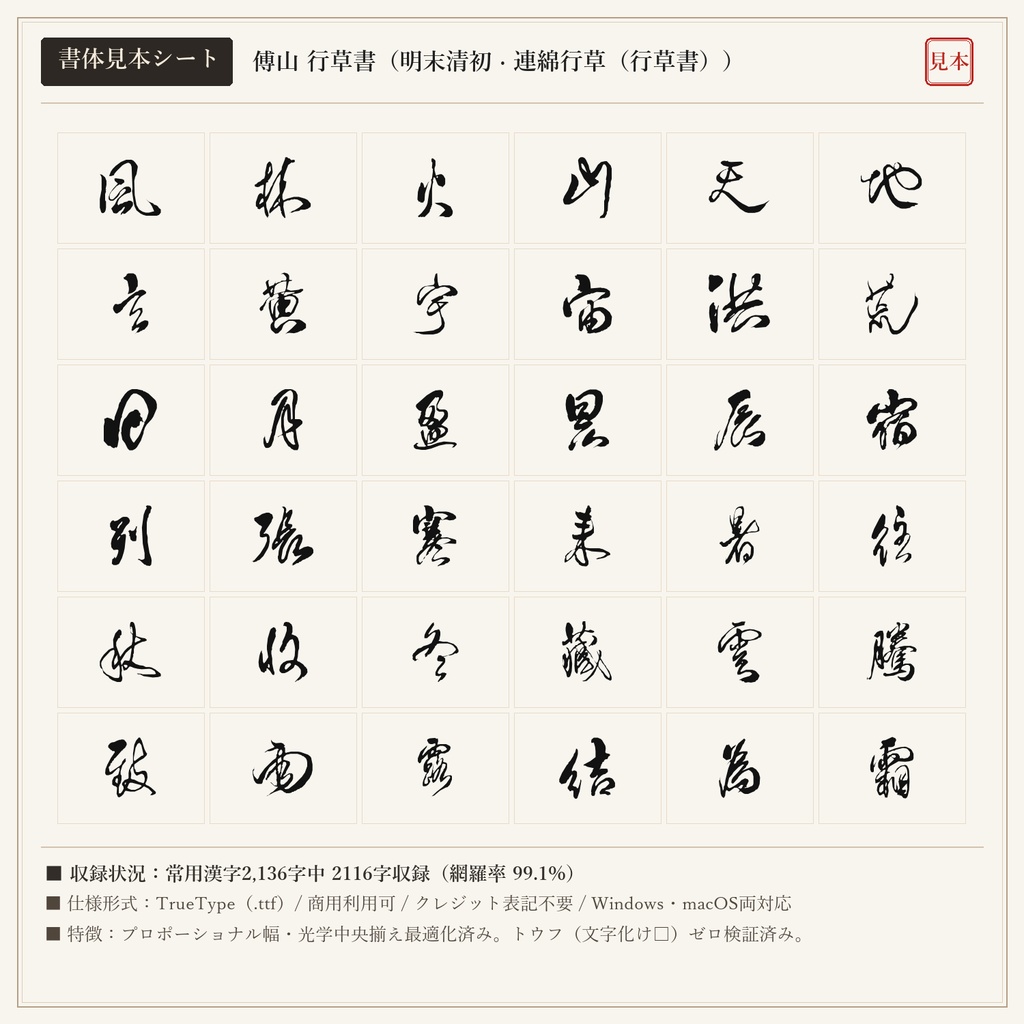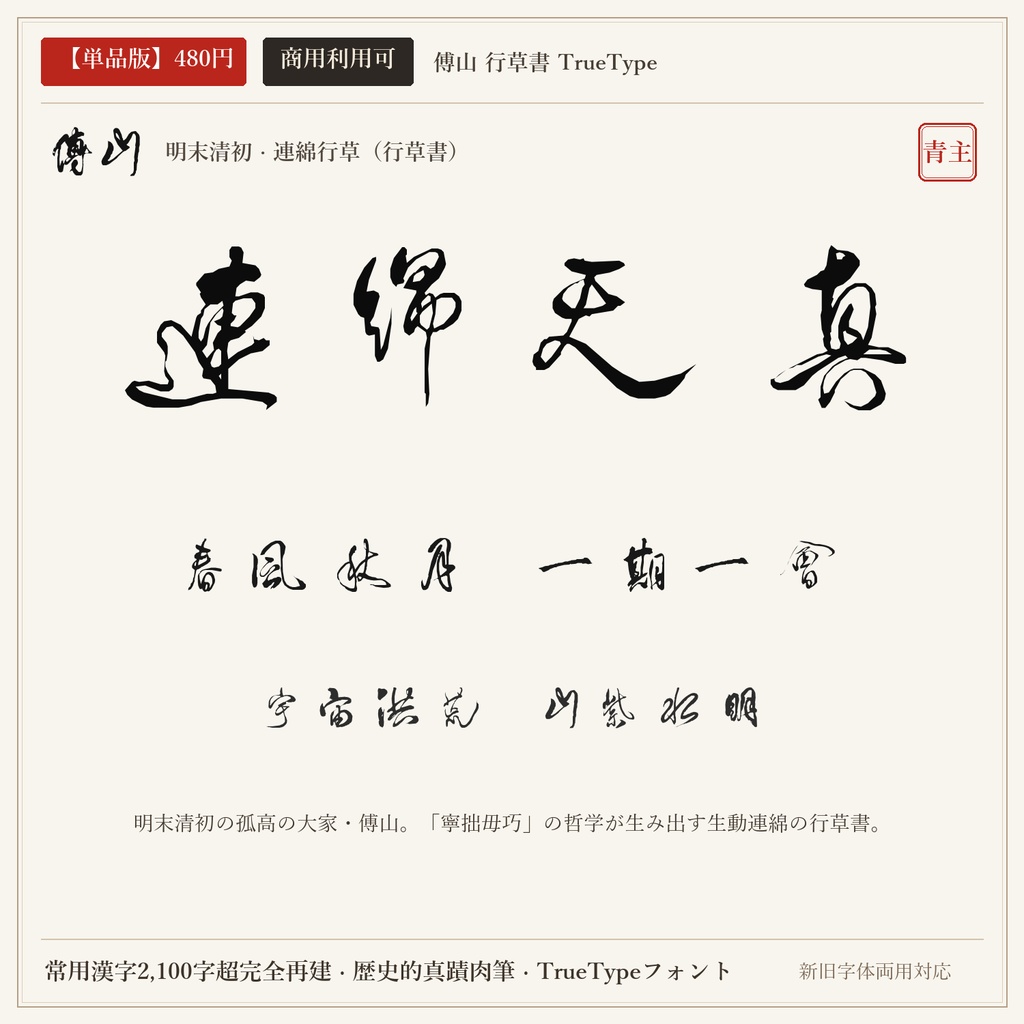
【単品版】傅山 行草書フォント|四寧四毋・孤高連綿の草書美・商用利用可
明末清初の個性派文人・傅山の連綿行草書から制作されたフォントです。「巧緻たるよりは拙なるべし」という四寧四毋の精神のもと、技巧にとらわれない天真爛漫な筆致とダイナミックな連綿美を堪能できます。 ■ 本フォントの特徴 ・常用漢字2,136字中、2116字を高精度収録(網羅率 99.1%)。 ・現代の新字体を入力しても、歴史的な真蹟字形・旧字体が自然に出力されるデュアルマッピング対応。 ・文字ごとの最適なプロポーショナル字幅設定により、自然で流麗な連綿と墨の息遣いを再現。 ・トウフ(文字化け□)を出さない事前フォントマッピング検証済み。 ■ 未収録文字一覧(全20字) 歴史的真蹟・拓本に存在しない以下の字種は未収録(非対応)となります。ご購入前にご確認ください。 丼 刹 咲 唄 堀 峠 拶 枠 栃 桁 濫 疎 線 脊 菓 著 込 郷 闘 駄 ■ 形式 TrueTypeフォント(TTF) / Windows・macOS両対応 ■ 利用規約 個人・法人の商用利用OK。クレジット表記不要。 ロゴ、動画、ゲーム、書籍、同人誌、配信サムネイル、Web、印刷物、グッズ等に自由にご使用いただけます。 フォントファイル自体の再配布・共有・販売・転売は禁止です。 ※東晋の王羲之(行書)と盛唐の顔真卿(楷書)を同梱した「【無料版】王羲之 + 顔真卿 2書体セット(0円)」もショップ内にて無料配布中です。